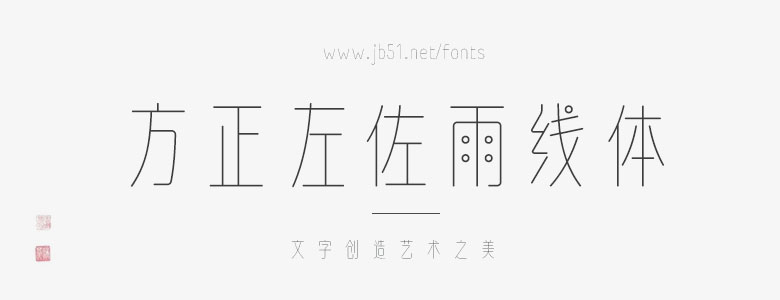
雨線體Rainline,筆畫為等線形式,結(jié)構(gòu)試圖在書寫與幾何之間找到平衡點,字面和曲線的風(fēng)格參考小篆,偏瘦長,接近黃金比。點似雨滴,線如雨簾,清新纖婉。風(fēng)格關(guān)鍵詞:知性、美妝、護(hù)膚、時尚、精致、科技產(chǎn)品、水、新媒體、互聯(lián)網(wǎng)等。